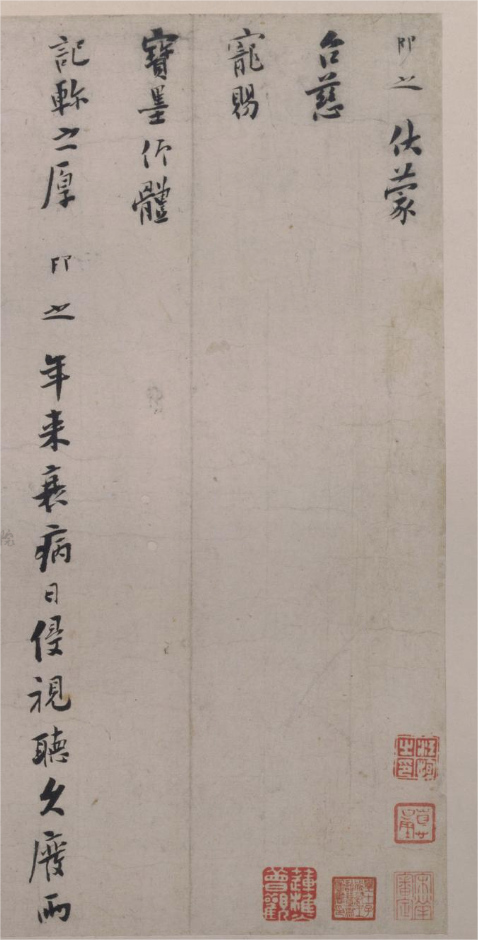
汉标张即之行书台慈帖 By 真迹小字库 商用字体
字体全名: 汉标张即之行书台慈帖
字体简介: 下载须知:本字库非标准GB2312字库。本字库只包含了张即之《台慈帖》真迹上的“128个字”。本幅有宋荦、江恂、成亲王、潘仕成、绵亿等人鉴藏印。《台慈帖》,宋,张即之书,纸本,册页,1页,纵30.9厘米,横43.1厘米。此帖内容为应酬类信札。结衔称“致仕”,应作于景定年间,为张氏老年之笔。《台慈帖》书法运笔提顿幅度明显,点划虚实相映,线条粗细变化与写经书颇似。结字严整奇伟,布白疏朗而有新意,确如文徵明所言:“即之,安国(张孝祥)之后……骨力健劲,大类安国所书,稍变而刻急,遂自名家。”清李佐贤《书画鉴影》著录,文物出版社《宋人书翰》册影印,刻《海山仙馆藏真帖》。